你只知道Helvetica,但这些经典的英文字体它们怎么用才对?
前篇怎样正确使用经典英文字体,不让它变为“菜市场字”?,我们介绍了两款精典欧文字体,一款是优雅代表、官方使用率最高的Optima,以及设计师的最爱Helvetica,本篇将再介绍两款经典字体,带大家了解其设计特色及如何正确使用。
Futura 跨领域的安全牌
字体设计者Paul Renner 说:「真正的现代,是如实地表达客观的时代精神。真正的现代,是经得起时间考验的完美,只是,这也仅仅是我们现在的看法,并不适用于所有时期,因为每一代人对于什么才经得起考验,都有不同的定义。」而Futura 就是由Paul Renner 于1927 年所设计的字体。
Futura 的几何构造、没有人文轴心的特色强烈,可以说是理性逻辑与感性风格兼备,是许多设计师的入门款,意思是说,如果你正在寻找有设计感、表情特殊的字体,但又对字体认识不那么多,那其中一个安全的选项就是Futura,因为这个字体够经典,容易驾驭。与 Helvetica 不同的是,设计师并不是没有想法,但可能是受限于对其他字体的了解,因此才选择它了。
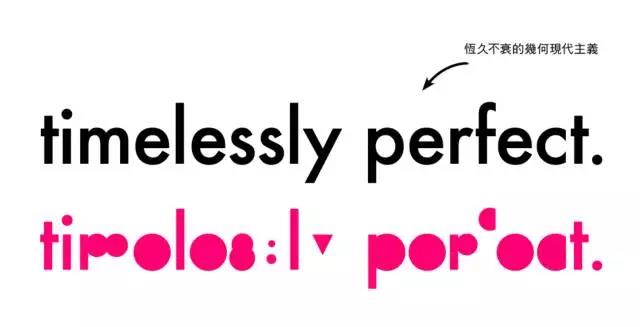
富节奏感的 Futura
另外,参考Futura 的几何造型而衍生的设计也不少,许多国际知名的品牌识别就是以Futura为基础发展字体,像是Chanel、LouisVuitton、Nike、Adidas 都是Futura 爱用者,所以当然曝光度与辨识度也非常高。确实,Futura 有它非常好用的地方,独特的几何构造设计作为标题时装饰性强,而大小写字高的比例虽然反差大,却是非常协调舒适的,保有足够的起伏,做为内文字使用也有很好的节奏感与阅读性,因此,如果内容属性合适的情况下(不是所有内容),Futura不失为一个理想的选择。
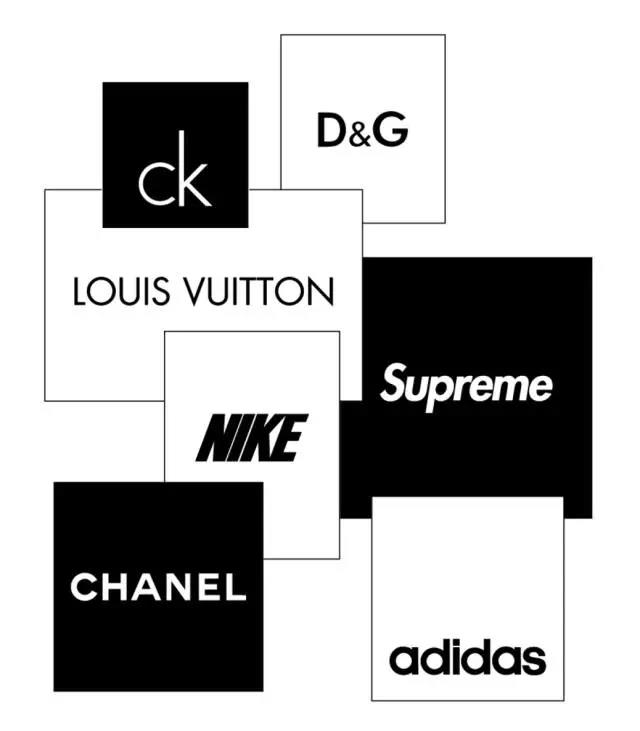
类似字体也不错用
如果你也看腻了这将近九十岁的字体,有什么其他选项呢?与Futura原理接近的设计其实也不少,如Kabel(Rudolf Koch,1927-1930)有极高的大小写反差,也有着高挑优雅的身段,而字体表现主义的代表设计师Herb Lublin在1970年发表的Avant Garde Gothic(& Tom Carnase)有非常特殊的连字字元,表情丰富夸张,以上这两者都很适合作为标题字使用;而Adrian Frutiger 的Avenir(1988)也是几何表现的经典之一,并且适用于标题与内文字。
Garamond 艺文圈的主角
即使都贴了「Garamond」的标签,这里指的并不是某个特定的字体,而是一种衬线字体类型的总称,原始的设计来自于十六世纪法国铸造师Claude Garamond,但大部分的Garamond字体其实是后来由Jean Jannon 刻画的。不同公司出品的版本都有不同的诠释,有些是大小写反差不同,有些则是笔画以及结构细节的差异,也有些是用了这个名字但血缘不同,例如下图中的ITC Garamond 其实是从Caslon衍生的:
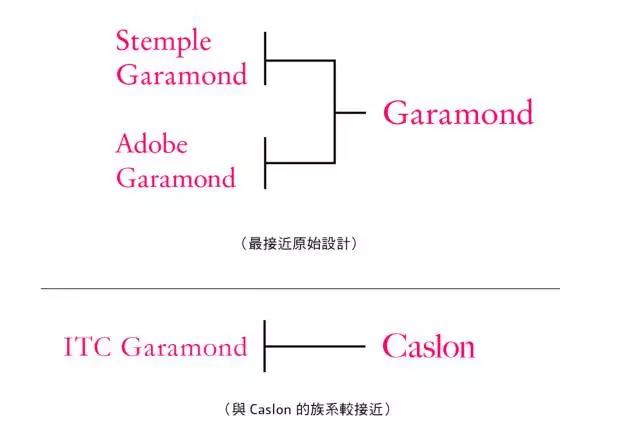
Stempel & Adobe Garamond 特别常见于表演艺术类的视觉上,尤其是当要强调日期时。整体来说,这类型字体不如前面所述的三个使用率普遍,也比较不容易犯错,的确也是非常适合用于内文字,尤其是数字确实很适合放大作为装饰,不过,各式各样不同时代或类型的内容,音乐的、戏剧的、现代的、古典的,都是千篇一律用同样的字体来诠释,可以说是一个非常特殊的现象,但是仔细想想,除了经济与省时的考量以外,似乎是缺乏设计上的正当性,字体的选用不一定有考量到与内容之间的关联性,或者是同时出现的不同字体的协调性。
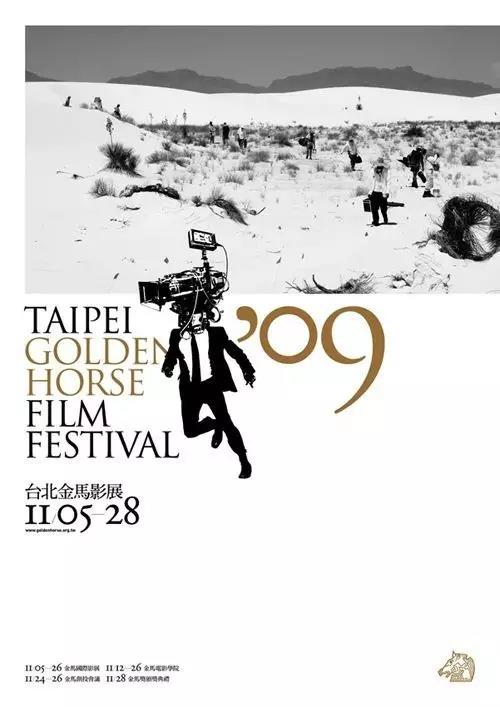
金马影展海报
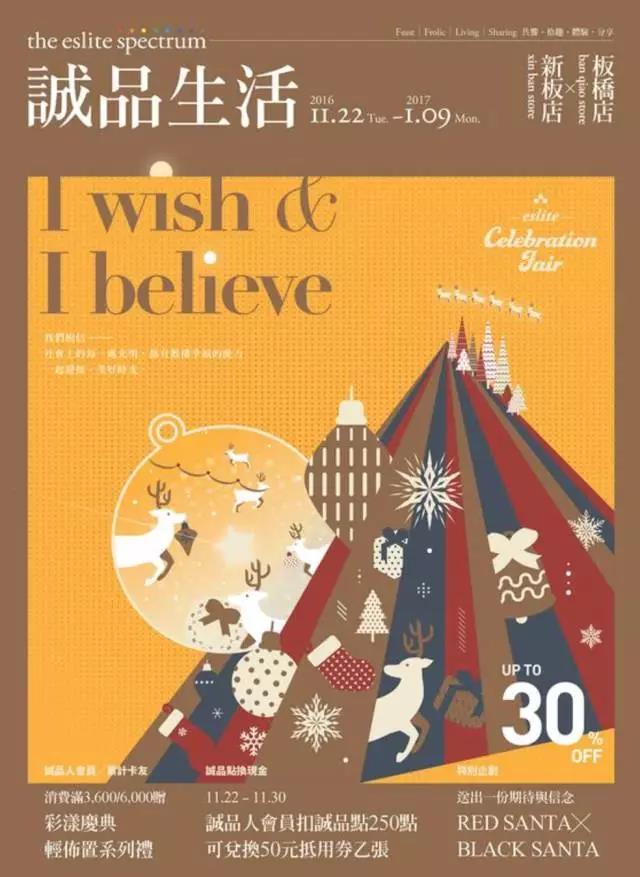
诚品也是 Garamond 的爱用者,文宣上经常可以看得到。
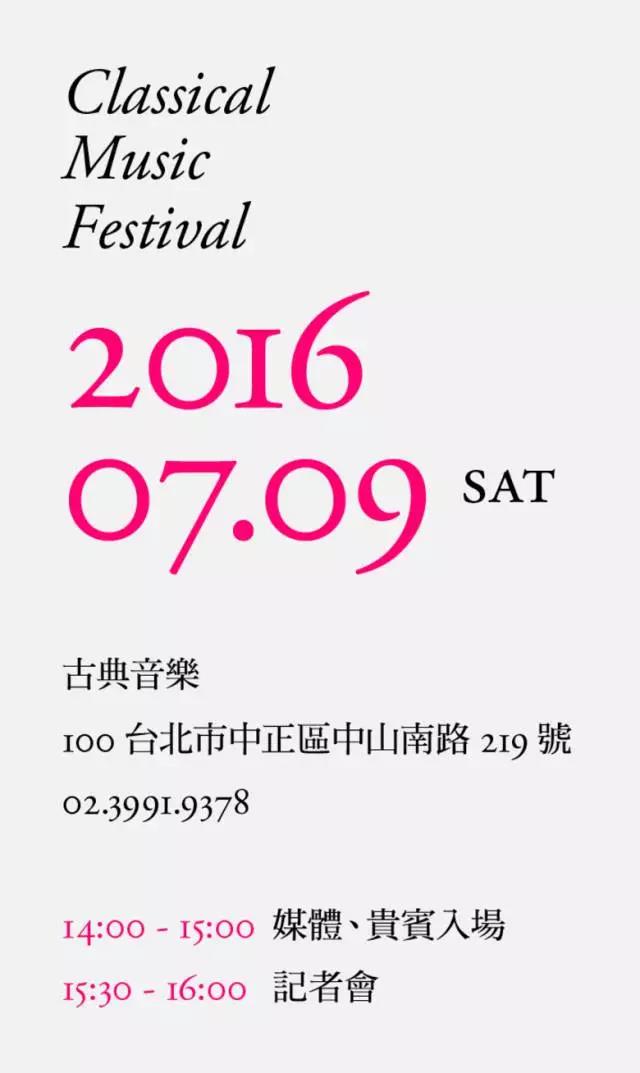
类似字体也不错用
不过,一般人也不太能分辨不同衬线字体之间的差异,或许是不知道如何选择,也可能是选择不多的原因,跳脱不了 Garamond 或是其他古典主义的范围。其实受到 Garamond 影响或启发的字体不少,例如 Jan Tshichold 在1966年设计的 Sabon、Dante(Giovanii Mardersteig,1952)与 Bembo(Monotype,1969)。在数位时期之后出现的衬线字体设计也很多,例如Robert Slimbach 的Minion(1989);Petr van Blokland 的Proforma(1994),或是Martin Majoor 的Scala(1990s);另外,同时具备人文主义的风格与优雅的数字表现字体则有:法国血统的Fournier(Pierre-Simon Fournier,1924)或Le Monde Livre(Jean François Porchez,1997-2008),建议设计师不妨根据内容的属性,试着做出跳脱传统的选择。
大胆前卫的字体易被冷落
上面列出我们周遭常见使用的少数几个例子,但并不是仅止于此,随便走走看看就会看到许多如Bodoni、Palatino、DIN、Meta、Ms.Eveas 这些颇具特定时代感或潮流的字体出现,但即使大胆前卫如Emigre、Neville Brody、David Carson 在九〇末至两千年初所尝试的许多突破性字体或版面编排设计,在红极一时之后也冷静下来很久了,虽然它们的历史地位无可动摇,实验精神很值得欣赏学习,但因为时代感过于明显,当代的设计师反而很少使用。
Emigre 杂志第 70 期跨页设计
Neville Brody 于1992 年所设计的字体 FF Blur,海报由 Dario Dezfuli Rello 操刀
David Carson 所设计的 RAY GUN 杂志封面
如果有机会欣赏欧美国家的平面设计时,不妨也留意较少见、独特的字体设计,找出字体的名称及设计师,了解它的来由,慢慢累积作为使用上的参考,你会发现欧文字体的应用可能性非常宽阔,视觉发展的空间也是很大的。
最后再次提醒大家,经典或菜市场字体本身并不是错误,而是怎么使用的问题。经典与浮滥只在一线之间,如果是不知所以然的使用了,一味东施效颦,那就很难让人欣赏。当然如果你使用正确,或是在创新的环境条件下使用这些字体,那就是经典重现。字体也或许像流行一样,是反映时代的一种选择,每十年我们会看到迷你裙、喇叭裤回流的复古风,但是不是等大家都渐渐淡忘了之后,再重新诠释再出发会比较好?